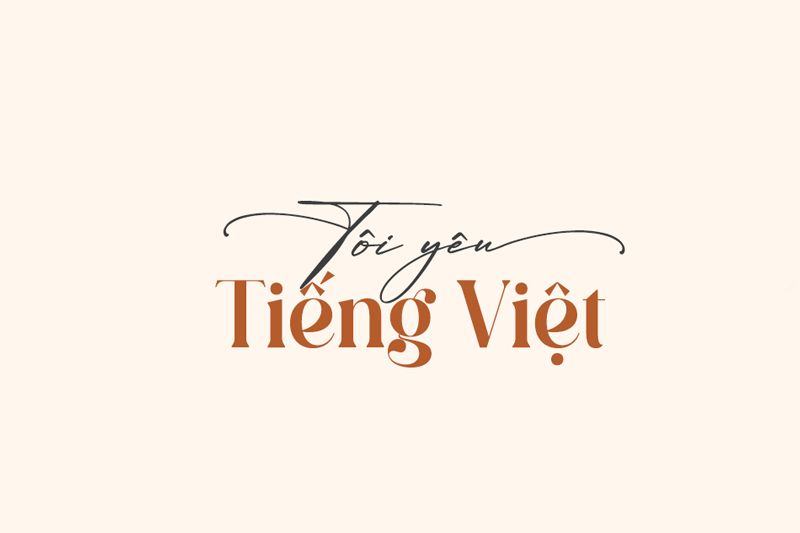
Font Chữ Việt Hóa Miễn Phí: Đẹp Mê Ly, Dùng Ngay Không Lo Lỗi (2025)
Bạn đang tìm kiếm Font Chữ Việt Hóa Miễn Phí đẹp mắt để thổi hồn vào thiết kế, nhưng lại lo lắng về lỗi font và bản quyền? Đừng lo, bài viết này sẽ giải quyết triệt để vấn đề đó! Chúng tôi sẽ chia sẻ danh sách font chữ Việt hóa đẹp mê ly, tải miễn phí, đảm bảo không lỗi, kèm theo hướng dẫn cài đặt chi tiết. Khám phá ngay những kiểu chữ độc đáo, phù hợp với mọi dự án từ thiết kế logo, ấn phẩm quảng cáo đến nội dung websitemạng xã hội. Đồng thời, bạn cũng sẽ nắm vững các lưu ý quan trọng về bản quyền để sử dụng font một cách an toàn và hiệu quả. Hãy cùng Blog khám phá thế giới font chữ đầy sáng tạo này!
Font Chữ Việt Hóa Miễn Phí: Tìm Kiếm, Tải Về & Sử Dụng Hiệu Quả 2025
Việc tìm kiếm, tải về và sử dụng font chữ Việt hóa miễn phí hiệu quả là một nhu cầu thiết yếu đối với các nhà thiết kế, người làm sáng tạo nội dung và cả người dùng văn phòng trong năm 2025. Để đáp ứng nhu cầu thiết kế và soạn thảo văn bản ngày càng cao, việc lựa chọn và sử dụng đúng cách các font chữ Việt hóa miễn phí không chỉ giúp nâng cao tính thẩm mỹ mà còn đảm bảo trải nghiệm người dùng tốt nhất.
Việc tiếp cận font Việt hóa miễn phí mở ra cơ hội sáng tạo đa dạng cho nhiều đối tượng. Từ học sinh, sinh viên, đến các freelancer và doanh nghiệp nhỏ, ai cũng có thể tận dụng nguồn tài nguyên này để tạo ra những sản phẩm thiết kế và nội dung ấn tượng. Tuy nhiên, để sử dụng font chữ Việt hóa một cách hiệu quả, cần nắm vững các bước tìm kiếm, tải về và cài đặt, đồng thời hiểu rõ về vấn đề bản quyền và các lỗi thường gặp.
Font Chữ Việt Hóa Miễn Phí: Đẹp Mê Ly, Dùng Ngay Không Lo Lỗi (2025)
Vậy, làm thế nào để tìm kiếm font chữ Việt hóa miễn phí một cách nhanh chóng và chính xác?
Việc sử dụng font chữ Việt hóa miễn phí hiệu quả không chỉ dừng lại ở việc tìm kiếm và cài đặt. Bạn cần lưu ý đến một số yếu tố quan trọng khác để đảm bảo trải nghiệm tốt nhất:
• Lựa chọn font phù hợp với mục đích sử dụng: Mỗi font chữ có một phong cách và cá tính riêng. Hãy chọn font phù hợp với nội dung và thông điệp bạn muốn truyền tải. Ví dụ, font sans-serif thường phù hợp với thiết kế hiện đại, trong khi font serif thích hợp với văn bản trang trọng.
• Đảm bảo tính dễ đọc: Chọn font có kích thước và khoảng cách dòng phù hợp để đảm bảo người đọc có thể đọc nội dung một cách dễ dàng và thoải mái.
• Kiểm tra kỹ trước khi sử dụng: Sau khi cài đặt, hãy kiểm tra font chữ trong các ứng dụng khác nhau để đảm bảo nó hiển thị đúng cách và không gặp lỗi.
Bằng cách nắm vững các bước tìm kiếm, tải về và sử dụng, cũng như lưu ý đến các yếu tố quan trọng, bạn có thể tận dụng tối đa lợi ích của font chữ Việt hóa miễn phí trong công việc và học tập, đồng thời tạo ra những sản phẩm thiết kế và nội dung chất lượng cao.
Top 15+ Font Việt Hóa Miễn Phí Đẹp Nhất 2025 Cho Thiết Kế & Văn Bản
Việc lựa chọn font chữ Việt hóa miễn phí phù hợp đóng vai trò then chốt trong việc nâng tầm thẩm mỹ và truyền tải thông điệp hiệu quả cho các ấn phẩm thiết kế và văn bản năm 2025. Top font Việt hóa miễn phí đẹp nhất dưới đây được tuyển chọn kỹ lưỡng, đáp ứng đa dạng phong cách thiết kế, từ hiện đại đến cổ điển, giúp bạn dễ dàng tìm thấy “người bạn đồng hành” ưng ý cho mọi dự án. Các font chữ này không chỉ hỗ trợ đầy đủ tiếng Việt mà còn được chăm chút về mặt thẩm mỹ, mang đến sự chuyên nghiệp và thu hút cho các sản phẩm sáng tạo.
Việc tìm kiếm font chữ Việt hóa miễn phí đẹp và chất lượng có thể tốn nhiều thời gian, vì vậy danh sách này được tạo ra để giúp bạn tiết kiệm thời gian và công sức. Mỗi font chữ sẽ được giới thiệu ngắn gọn về phong cách, ứng dụng phù hợp, và điểm đặc biệt, giúp bạn dễ dàng đưa ra lựa chọn phù hợp với nhu cầu thiết kế.
Dưới đây là danh sách hơn 15 font chữ Việt hóa miễn phí hàng đầu, được dự đoán sẽ thịnh hành trong năm 2025, thích hợp cho cả thiết kế và sử dụng trong văn bản:
1. Roboto: Font sans-serif hiện đại, dễ đọc, phù hợp với nhiều loại dự án.
2. Open Sans: Font sans-serif phổ biến, thanh lịch, thích hợp cho cả tiêu đề và nội dung.
3. Lato: Font sans-serif tròn trịa, thân thiện, tạo cảm giác gần gũi.
4. Montserrat: Font hình học sans-serif, mạnh mẽ, cá tính, thường dùng cho thiết kế web và logo.
5. Oswald: Font sans-serif đậm, phù hợp với tiêu đề lớn, tạo sự chú ý.
6. Merriweather: Font serif cổ điển, trang trọng, lý tưởng cho sách và tạp chí.
7. Lora: Font serif thanh lịch, hiện đại, dễ đọc trên màn hình, thích hợp cho blog và website.
8. Playfair Display: Font serif cách điệu, sang trọng, thường dùng cho tiêu đề và logo.
9. Archivo: Font hình học sans-serif, dễ đọc ở nhiều kích cỡ, phù hợp cho thiết kế ứng dụng và giao diện người dùng.
10. Nunito: Font sans-serif tròn trịa, vui nhộn, thích hợp cho trẻ em và các dự án sáng tạo.
11. Cabin: Font sans-serif hiện đại, cân đối, dễ đọc, phù hợp với nhiều loại thiết kế.
12. pháp luật: Font serif cổ điển, mạnh mẽ, cá tính, thích hợp cho các ấn phẩm in ấn và thiết kế retro.
13. SVN-Gilroy: Font sans-serif hiện đại, đa dạng kiểu dáng, được nhiều nhà thiết kế ưa chuộng.
14. Be Vietnam Pro: Font sans-serif thanh lịch, dễ đọc, hỗ trợ tốt tiếng Việt.
15. Lexend Deca: Font được thiết kế đặc biệt để cải thiện khả năng đọc, phù hợp cho người có vấn đề về thị lực.
16. Comfortaa: Font sans-serif tròn trịa, mềm mại, tạo cảm giác thoải mái và dễ chịu.
Nguồn Tải Font Việt Hóa Miễn Phí Uy Tín & An Toàn: Tránh Virus & Lỗi Font
Việc tìm kiếm và sử dụng font chữ Việt hóa miễn phí đẹp mắt là nhu cầu thiết yếu của nhiều nhà thiết kế và người dùng văn phòng, tuy nhiên, điều quan trọng là phải tìm được nguồn tải font uy tín để đảm bảo an toàn cho thiết bị và tránh các lỗi font không mong muốn. Việc lựa chọn sai nguồn có thể dẫn đến nguy cơ lây nhiễm virus, mã độc, hoặc gặp phải các lỗi font ảnh hưởng đến chất lượng thiết kế và văn bản.
Hiện nay, có rất nhiều website cung cấp font Việt hóa miễn phí, nhưng không phải tất cả đều đáng tin cậy. Để đảm bảo an toàn, người dùng nên ưu tiên các trang web có uy tín, được cộng đồng đánh giá cao và có chính sách bảo mật rõ ràng. Bên cạnh đó, việc kiểm tra kỹ lưỡng các font trước khi cài đặt cũng là một bước quan trọng để phòng tránh các rủi ro tiềm ẩn.
Dưới đây là một số gợi ý về nguồn tải font Việt hóa miễn phí uy tín và an toàn, giúp bạn an tâm sử dụng trong các dự án thiết kế và soạn thảo văn bản:
• Google Fonts: Thư viện font khổng lồ của Google cung cấp nhiều font hỗ trợ tiếng Việt, được cập nhật thường xuyên và đảm bảo chất lượng. Ưu điểm: dễ sử dụng, tích hợp sẵn vào nhiều ứng dụng.
• Font Squirrel: Website chuyên cung cấp font miễn phí cho mục đích thương mại, với nhiều font Việt hóa chất lượng cao. Ưu điểm: Giấy phép sử dụng rõ ràng, nhiều font độc đáo.
• Behance: Nền tảng sáng tạo nổi tiếng, nơi các nhà thiết kế thường chia sẻ font Việt hóa miễn phí do họ tự tạo ra. Ưu điểm: Nhiều font độc đáo, sáng tạo, hỗ trợ trực tiếp từ tác giả.
• DaFont: Một trong những website cung cấp font miễn phí lớn nhất, với nhiều lựa chọn font Việt hóa từ nhiều nguồn khác nhau. Lưu ý: Cần kiểm tra kỹ giấy phép sử dụng trước khi dùng cho mục đích thương mại.
• Type Department: Dự án Việt hóa font nổi tiếng, cung cấp nhiều font Việt hóa chất lượng cao, được chăm chút kỹ lưỡng về mặt kỹ thuật và thẩm mỹ. Ưu điểm: Font chất lượng cao, hỗ trợ tốt tiếng Việt.
• 1001 Free Fonts: Trang web cung cấp hàng ngàn font miễn phí, bao gồm cả font Việt hóa. Lưu ý: Cần cẩn trọng khi tải font từ trang web này vì có thể chứa quảng cáo hoặc phần mềm không mong muốn.
Để đảm bảo an toàn khi tải và sử dụng font Việt hóa miễn phí, bạn nên:
• Kiểm tra kỹ thông tin về font: Đọc kỹ mô tả font, giấy phép sử dụng, và đánh giá của người dùng trước khi tải về.
• Quét virus trước khi cài đặt: Sử dụng phần mềm diệt virus để quét các file font vừa tải về trước khi cài đặt.
• Tải font từ nguồn uy tín: Chỉ tải font từ các website được đánh giá cao về độ tin cậy và an toàn.
• Sao lưu font gốc: Sao lưu các font hiện có trên hệ thống trước khi cài đặt font mới để tránh trường hợp xảy ra lỗi.
• Cập nhật phần mềm diệt virus thường xuyên: Đảm bảo phần mềm diệt virus luôn được cập nhật phiên bản mới nhất để phát hiện và loại bỏ các mối đe dọa tiềm ẩn.
Bằng cách lựa chọn nguồn tải font cẩn thận và tuân thủ các biện pháp phòng ngừa, bạn có thể thoải mái sử dụng font chữ Việt hóa miễn phí mà không lo lắng về vấn đề an toàn và chất lượng.
Hướng Dẫn Cài Đặt Font Việt Hóa Trên Windows, macOS & Các Ứng Dụng Phổ Biến
Việc cài đặt font Việt hóa không chỉ giúp bạn đọc và soạn thảo văn bản tiếng Việt một cách chính xác mà còn mang đến trải nghiệm thiết kế chuyên nghiệp hơn; sau đây là hướng dẫn chi tiết cách cài đặt font chữ Việt hóa miễn phí trên các hệ điều hành và ứng dụng phổ biến nhất hiện nay. Quá trình cài đặt font chữ khá đơn giản, nhưng đối với người mới bắt đầu, việc nắm rõ các bước thực hiện sẽ giúp tránh được các lỗi không mong muốn. Việc cài đặt font Việt hóa này sẽ giúp hiển thị đúng các ký tự tiếng Việt, tránh tình trạng lỗi font, đặc biệt quan trọng khi sử dụng các font thiết kế độc đáo.
Để đảm bảo trải nghiệm sử dụng font Việt hóa mượt mà, dưới đây là hướng dẫn chi tiết cho từng nền tảng:
• Cài đặt Font Việt Hóa trên Windows:
1. Cách 1: Cài đặt nhanh chóng:
• Mở thư mục chứa font chữ đã tải về.
• Click chuột phải vào file font.
• Chọn “Install” (Cài đặt).
2. Cách 2: Cài đặt thông qua thư mục Fonts:
• Mở Control Panel (Bảng điều khiển).
• Chọn “Appearance and Personalization” (Giao diện và Cá nhân hóa).
• Chọn “Fonts” (Phông chữ).
• Kéo và thả file font Việt hóa vào thư mục “Fonts”. Windows sẽ tự động cài đặt font.
• Cài đặt Font Việt Hóa trên macOS:
1. Sử dụng Font Book:
• Mở ứng dụng Font Book (có sẵn trong thư mục Applications/Utilities).
• Kéo và thả file font vào cửa sổ Font Book.
• Hoặc, chọn “File” > “Add Fonts…” (Tệp > Thêm Phông chữ…) và chọn file font.
2. Xác nhận cài đặt:
• Font Book sẽ hiển thị thông tin về font chữ, nhấn “Install Font” (Cài đặt Phông chữ) để hoàn tất.
• Cài đặt Font Việt Hóa trong Các Ứng Dụng Phổ Biến (Microsoft Word, Adobe Photoshop, Illustrator):
1. Sau khi cài đặt font vào hệ điều hành, các ứng dụng này sẽ tự động nhận diện font Việt hóa.
2. Khởi động lại ứng dụng nếu bạn đang mở nó trong quá trình cài đặt font.
3. Chọn font trong danh sách font chữ của ứng dụng. Lưu ý, tên font sẽ hiển thị theo tên của file font chữ bạn đã tải.
Việc cài đặt font Việt hóa thành công sẽ giúp bạn sử dụng font chữ một cách trơn tru trong các ứng dụng văn phòng, thiết kế.
Khắc Phục Lỗi Font Việt Hóa Thường Gặp: Hiển Thị Sai, Mất Chữ, Lỗi Encoding
Khi sử dụng font chữ Việt hóa miễn phí, người dùng đôi khi gặp phải các vấn đề như hiển thị sai, mất chữ hoặc lỗi encoding, gây ảnh hưởng đến trải nghiệm và chất lượng thiết kế. Việc hiểu rõ nguyên nhân và cách khắc phục những lỗi này là rất quan trọng để đảm bảo font Việt hóa hoạt động trơn tru trên mọi nền tảng và ứng dụng.
Một trong những nguyên nhân phổ biến nhất dẫn đến lỗi font Việt hóa là do thiếu font hoặc font bị hỏng. Đôi khi, font bạn tải về chưa được cài đặt đúng cách hoặc bị lỗi trong quá trình tải. Để khắc phục, hãy thử tải lại font từ một nguồn uy tín, sau đó kiểm tra xem font đã được cài đặt thành công trên hệ thống chưa. Nếu font đã được cài đặt nhưng vẫn gặp lỗi, hãy thử gỡ cài đặt và cài đặt lại.
Lỗi encoding cũng là một vấn đề thường gặp, đặc biệt khi làm việc với các phần mềm cũ hoặc các định dạng file khác nhau. Encoding là cách mà máy tính diễn giải các ký tự, và nếu font của bạn không tương thích với encoding được sử dụng, các ký tự tiếng Việt có thể bị hiển thị sai hoặc biến thành các ký tự lạ. Để giải quyết vấn đề này, bạn có thể thử thay đổi encoding của file hoặc ứng dụng bạn đang sử dụng sang UTF-8, một encoding phổ biến và hỗ trợ đầy đủ các ký tự tiếng Việt.
Ngoài ra, một số ứng dụng có thể yêu cầu bạn phải chọn font Việt hóa một cách thủ công trong phần cài đặt hoặc tùy chọn. Ví dụ, trong Microsoft Word, bạn cần vào File > Options > Advanced > Show document content và chọn font phù hợp trong mục Font Substitution. Việc này đảm bảo rằng ứng dụng sẽ sử dụng đúng font để hiển thị văn bản tiếng Việt.
Cuối cùng, xung đột font cũng có thể gây ra các vấn đề hiển thị. Nếu bạn có nhiều phiên bản của cùng một font hoặc các font tương tự nhau được cài đặt trên hệ thống, chúng có thể gây xung đột và dẫn đến lỗi hiển thị. Để khắc phục, hãy thử gỡ bỏ các font không cần thiết hoặc các phiên bản cũ của font.
Luật Bản Quyền Font Chữ: Sử Dụng Font Việt Hóa Miễn Phí Như Thế Nào Cho Đúng?
Việc sử dụng font chữ Việt hóa miễn phí ngày càng phổ biến, tuy nhiên, nắm vững luật bản quyền font chữ là yếu tố then chốt để tránh các rủi ro pháp lý không đáng có, đặc biệt trong bối cảnh tìm kiếm và sử dụng font chữ đẹp mắt, hợp xu hướng cho thiết kế và văn bản ngày càng tăng. Vậy, làm thế nào để sử dụng font Việt hóa miễn phí một cách hợp pháp và an toàn?
Để sử dụng font chữ Việt hóa một cách đúng luật, người dùng cần hiểu rõ về các loại giấy phép (license) khác nhau đi kèm với mỗi font chữ. Phần lớn các font chữ miễn phí đều đi kèm với các điều khoản sử dụng cụ thể, quy định rõ phạm vi sử dụng cho phép, ví dụ như sử dụng cho mục đích cá nhân, phi thương mại, hoặc thương mại với một số giới hạn nhất định. Việc không tuân thủ các điều khoản này có thể dẫn đến các vấn đề pháp lý nghiêm trọng, bao gồm việc bị yêu cầu bồi thường thiệt hại.
Hiểu Rõ Các Loại Giấy Phép Font Chữ Phổ Biến
Việc phân biệt các loại giấy phép sẽ giúp bạn sử dụng font chữ Việt hóa một cách an toàn và hợp pháp:
• Giấy phép OFL (Open Font License): Đây là loại giấy phép phổ biến nhất cho font chữ miễn phí. Nó cho phép bạn sử dụng, sửa đổi và phân phối lại font chữ, kể cả cho mục đích thương mại. Tuy nhiên, bạn cần giữ nguyên thông tin bản quyền gốc và tuân thủ các điều khoản cụ thể của giấy phép.
• Giấy phép Creative Commons (CC): Một số font chữ được phát hành theo giấy phép Creative Commons. Giấy phép này có nhiều phiên bản khác nhau, với các điều khoản sử dụng khác nhau. Bạn cần kiểm tra kỹ các điều khoản của từng phiên bản để đảm bảo tuân thủ. Ví dụ, một số giấy phép CC có thể yêu cầu bạn ghi công tác giả, hoặc cấm sử dụng cho mục đích thương mại.
• Giấy phép độc quyền: Một số font chữ được cung cấp miễn phí nhưng vẫn thuộc quyền sở hữu của nhà thiết kế hoặc công ty. Trong trường hợp này, bạn cần tuân thủ các điều khoản sử dụng mà họ đưa ra, thường sẽ có những hạn chế nhất định về mục đích sử dụng, số lượng người dùng, hoặc phạm vi dự án.
Kiểm Tra Giấy Phép Font Chữ Trước Khi Sử Dụng
Trước khi sử dụng bất kỳ font chữ Việt hóa miễn phí nào, hãy luôn kiểm tra giấy phép đi kèm để đảm bảo bạn hiểu rõ các điều khoản sử dụng.
• Đọc kỹ tài liệu đi kèm: Các font chữ thường đi kèm với một tập tin văn bản chứa thông tin về giấy phép. Hãy đọc kỹ tài liệu này để hiểu rõ các quyền và nghĩa vụ của bạn.
• Kiểm tra trên website của nhà thiết kế: Nếu bạn tải font chữ từ website của nhà thiết kế, hãy tìm thông tin về giấy phép trên trang web đó.
• Sử dụng công cụ kiểm tra giấy phép: Có một số công cụ trực tuyến có thể giúp bạn kiểm tra giấy phép của font chữ.
Sử Dụng Font Chữ Cho Mục Đích Thương Mại: Những Lưu Ý Quan Trọng
Nếu bạn muốn sử dụng font chữ Việt hóa miễn phí cho mục đích thương mại, hãy đặc biệt cẩn trọng:
• Đảm bảo giấy phép cho phép: Kiểm tra kỹ giấy phép để đảm bảo nó cho phép sử dụng cho mục đích thương mại. Nếu không chắc chắn, hãy liên hệ với nhà thiết kế để xin phép.
• Ghi công tác giả: Nhiều giấy phép yêu cầu bạn ghi công tác giả khi sử dụng font chữ. Hãy đảm bảo bạn tuân thủ yêu cầu này.
• Không sửa đổi hoặc phân phối lại: Trừ khi giấy phép cho phép, bạn không được sửa đổi hoặc phân phối lại font chữ.
Tránh Các Nguồn Tải Font Chữ Lậu, Kém Uy Tín
Để đảm bảo an toàn pháp lý và tránh các vấn đề về virus, lỗi font, hãy chỉ tải font chữ Việt hóa miễn phí từ các nguồn uy tín như Google Fonts, Font Squirrel, hoặc website của các nhà thiết kế font chữ nổi tiếng. Tránh xa các website chia sẻ font chữ lậu, không rõ nguồn gốc. Việc sử dụng font chữ từ các nguồn này không chỉ vi phạm bản quyền mà còn tiềm ẩn nhiều rủi ro bảo mật.
Hiểu rõ và tuân thủ luật bản quyền font chữ là cách tốt nhất để bạn có thể thoải mái sáng tạo với font chữ Việt hóa miễn phí mà không phải lo lắng về các vấn đề pháp lý.
Font Việt Hóa & Thiết Kế Thương Hiệu: Lựa Chọn Font Phù Hợp, Tạo Dấu Ấn Riêng
Font Việt hóa đóng vai trò then chốt trong việc xây dựng thiết kế thương hiệu độc đáo và truyền tải thông điệp một cách hiệu quả đến thị trường Việt Nam, đặc biệt là trong bối cảnh thị trường font chữ Việt hóa miễn phí ngày càng phát triển. Việc lựa chọn font chữ Việt hóa phù hợp không chỉ đảm bảo tính thẩm mỹ, khả năng đọc mà còn thể hiện cá tính, giá trị cốt lõi của thương hiệu, góp phần tạo nên sự khác biệt so với đối thủ cạnh tranh. Vì vậy, doanh nghiệp cần cân nhắc kỹ lưỡng các yếu tố về phong cách, tính ứng dụng và đặc biệt là bản quyền khi lựa chọn font Việt hóa cho các ấn phẩm thương hiệu của mình.
Việc lựa chọn font chữ phù hợp là một quá trình đòi hỏi sự am hiểu về thiết kế, thị giác và cả tâm lý khách hàng. Một font chữ được lựa chọn kỹ càng không chỉ giúp truyền tải thông điệp một cách rõ ràng mà còn tạo ra ấn tượng mạnh mẽ và đáng nhớ cho thương hiệu. Hãy xem xét những yếu tố sau để tìm ra font chữ Việt hóa lý tưởng, góp phần xây dựng một thiết kế thương hiệu thành công:
• Xác định tính cách thương hiệu: Trước khi bắt đầu tìm kiếm font chữ, hãy xác định rõ tính cách mà bạn muốn thương hiệu của mình thể hiện. Thương hiệu của bạn trẻ trung, năng động hay chuyên nghiệp, đáng tin cậy? Một font chữ serif truyền thống có thể phù hợp với một thương hiệu luật sư, trong khi một font chữ sans-serif hiện đại có thể phù hợp hơn với một công ty công nghệ.
• Đảm bảo khả năng đọc: Một font chữ đẹp đến đâu cũng trở nên vô nghĩa nếu nó khó đọc. Hãy thử nghiệm font chữ trên nhiều kích cỡ và nền khác nhau để đảm bảo rằng nó vẫn dễ đọc ngay cả khi in nhỏ hoặc hiển thị trên màn hình.
• Tính nhất quán: Chọn một font chữ có nhiều biến thể (đậm, nghiêng, kích thước khác nhau) để bạn có thể sử dụng nó một cách nhất quán trên tất cả các ấn phẩm của thương hiệu, từ logo, website cho đến tài liệu quảng cáo.
• Kiểm tra bản quyền: Hãy chắc chắn rằng font chữ Việt hóa miễn phí mà bạn chọn được phép sử dụng cho mục đích thương mại. Nếu không, bạn có thể phải đối mặt với các vấn đề pháp lý nghiêm trọng.
Sử dụng font Việt hóa một cách sáng tạo trong thiết kế thương hiệu có thể tạo ra sự khác biệt đáng kể, đặc biệt khi kết hợp với các yếu tố thiết kế khác. Chẳng hạn, một thương hiệu thời trang có thể sử dụng một font chữ Việt hóa độc đáo, viết tay để tạo cảm giác cá nhân hóa và gần gũi, trong khi một công ty tài chính có thể chọn một font chữ sans-serif mạnh mẽ để thể hiện sự tin cậy và ổn định. Ngoài ra, việc sử dụng màu sắc, bố cục và hình ảnh hài hòa với font chữ cũng góp phần quan trọng trong việc xây dựng một thiết kế thương hiệu ấn tượng và dễ nhận diện.
Để minh họa rõ hơn về tầm quan trọng của việc lựa chọn font Việt hóa phù hợp cho thiết kế thương hiệu, hãy xem xét trường hợp của một số thương hiệu Việt Nam thành công. Ví dụ, Biti’s Hunter đã sử dụng một font chữ mạnh mẽ, hiện đại, thể hiện sự năng động và tinh thần đổi mới của thương hiệu. Vinamilk, mặt khác, sử dụng một font chữ tròn trịa, ấm áp, tạo cảm giác gần gũi, thân thiện với người tiêu dùng. Những ví dụ này cho thấy rằng, việc lựa chọn font chữ phù hợp có thể giúp thương hiệu truyền tải thông điệp một cách hiệu quả và tạo dựng mối liên kết cảm xúc với khách hàng.
[Case Study] Dự Án Sử Dụng Font Việt Hóa Miễn Phí Thành Công: Học Hỏi & Áp Dụng
Trong bối cảnh nhu cầu sử dụng font chữ Việt hóa miễn phí ngày càng tăng, việc phân tích và học hỏi từ các case study về dự án thành công là vô cùng quan trọng để có thể ứng dụng hiệu quả và tạo ra những thiết kế ấn tượng. Việc nghiên cứu dự án sử dụng font Việt hóa miễn phí thành công không chỉ giúp người dùng hiểu rõ hơn về tiềm năng của các font chữ này mà còn cung cấp những bài học kinh nghiệm quý báu trong việc lựa chọn và sử dụng font phù hợp.
Để hiểu rõ hơn về cách ứng dụng font chữ, hãy cùng khám phá các dự án đã thành công trong việc sử dụng font chữ Việt hóa miễn phí, từ đó rút ra những kinh nghiệm thực tiễn và áp dụng vào các dự án của riêng bạn.
• Nhận diện thương hiệu: Nhiều doanh nghiệp nhỏ và vừa đã thành công trong việc xây dựng nhận diện thương hiệu mạnh mẽ nhờ sử dụng font Việt hóa miễn phí độc đáo và phù hợp. Ví dụ, một quán cà phê sử dụng font SVN-Gilroy Việt hóa tạo cảm giác hiện đại, trẻ trung, thu hút giới trẻ. Hoặc một cửa hàng thủ công mỹ nghệ chọn font VNF-Bodik Việt hóa mang phong cách cổ điển, truyền thống, thể hiện sự tỉ mỉ và tinh tế.
• Thiết kế ấn phẩm truyền thông: Các tổ chức phi lợi nhuận thường tận dụng font Việt hóa miễn phí trong các thiết kế ấn phẩm truyền thông nhằm tiết kiệm chi phí mà vẫn đảm bảo tính thẩm mỹ và chuyên nghiệp. Ví dụ, một tổ chức bảo vệ môi trường sử dụng font Nunito Sans Việt hóa trong các poster, banner, infographic, truyền tải thông điệp một cách rõ ràng, dễ đọc.
• Sản phẩm số: Các blogger, YouTuber, và nhà sáng tạo nội dung thường sử dụng font Việt hóa miễn phí để tạo ra các thiết kế đồ họa, thumbnail, video hấp dẫn, thu hút người xem. Một kênh YouTube về du lịch sử dụng font Montserrat Việt hóa tạo sự năng động, hiện đại cho các video giới thiệu địa điểm du lịch.
Các yếu tố thành công của các dự án sử dụng font Việt hóa miễn phí bao gồm:
• Lựa chọn font phù hợp: Font chữ được lựa chọn phải phù hợp với phong cách, tính cách, và thông điệp của dự án.
• Sử dụng font nhất quán: Tính nhất quán trong việc sử dụng font chữ giúp tạo dựng nhận diện thương hiệu và tăng tính chuyên nghiệp cho thiết kế.
• Kết hợp font hài hòa: Việc kết hợp các font chữ khác nhau một cách hài hòa có thể tạo ra hiệu ứng thị giác độc đáo và thu hút.
• Tối ưu hóa hiển thị: Font chữ cần được tối ưu hóa để hiển thị tốt trên các thiết bịnền tảng khác nhau.